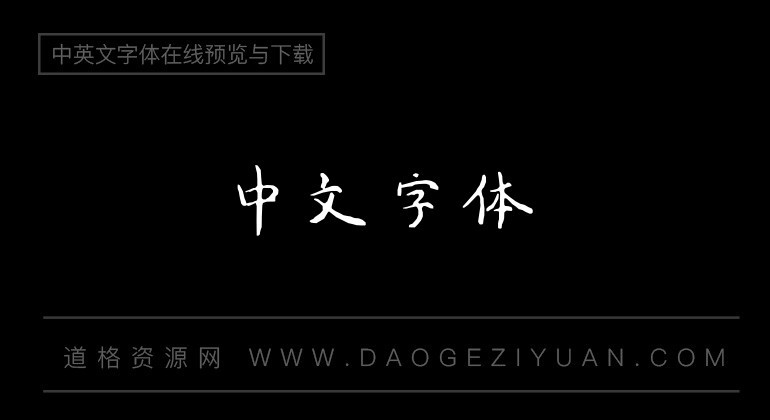
荼蘼花开是一款古朴大气的中文字体,它的字体风格细腻、精致、清新、古典,适合用于结婚纪念册、明信片、古装剧片等场合。荼蘼花开字体的字形简洁大方,字体的笔画细腻清晰,笔画间距合理,构成了一种清新大气、古朴典雅的字体风格。文件名:HuaKai-2.ttf
荼蘼花开是一款非常不错的手写艺术字体,具有很好的视觉感,适合于文化类的宣传设计、商业类品牌的广告和产品包装设计以及个性化文字排版等较多场景。